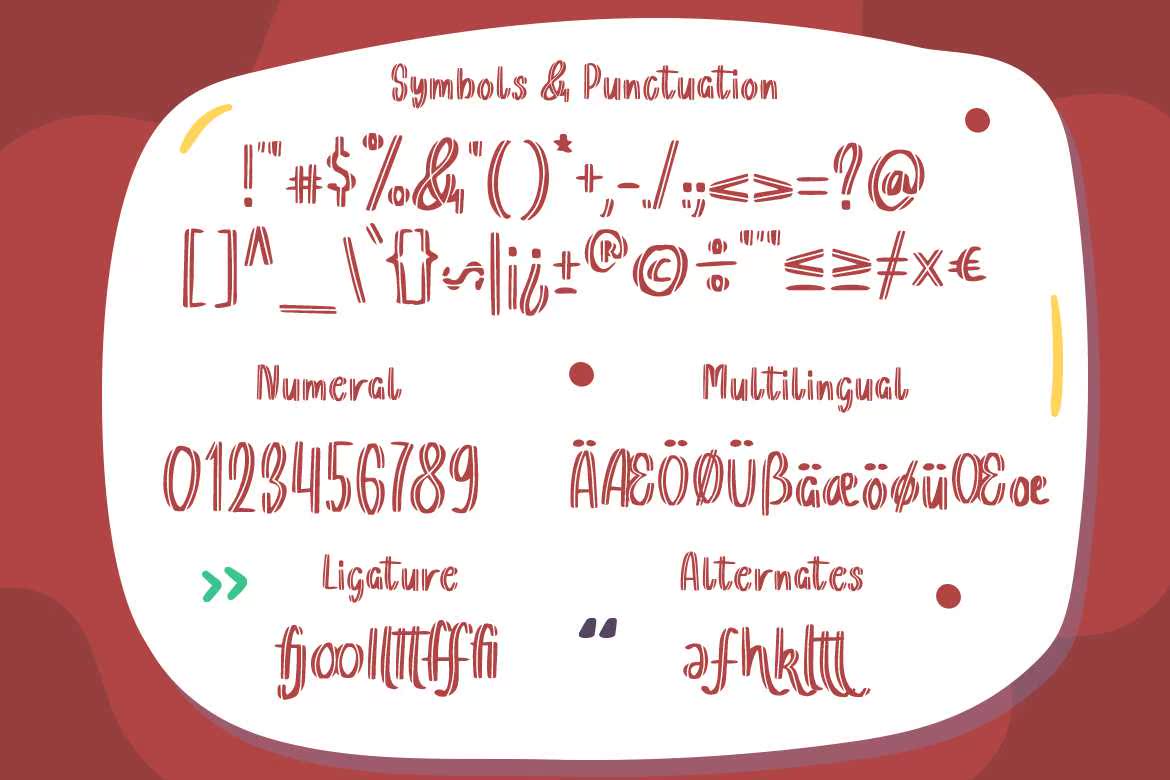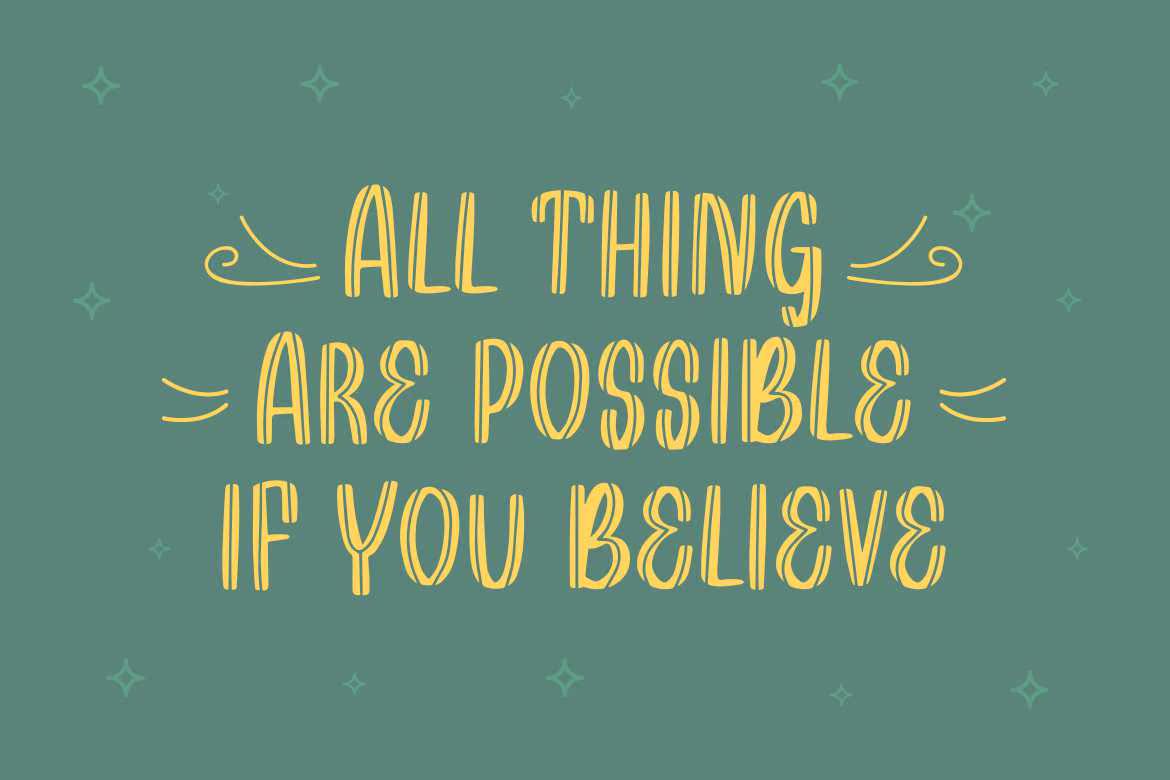
Savonburg是一种外观有趣的显示字体。该字形由两个具有装饰感的同心路径构成。这一原创的所有字体将出现在各种各样的字体上,从字体和标题、包装、品牌、报价、邀请卡、礼品卡、,ToStationary.FullVersionDownloadHere:Savonburgisanawesomelookingplayfulldisplay字体。该字形由两个具有装饰感的同心路径构成。此原始Allook将出现在各种各样的字体上,从字体和标题、包装、品牌、报价、邀请卡、礼品卡到Stationary。FullVersionDownloadHere: